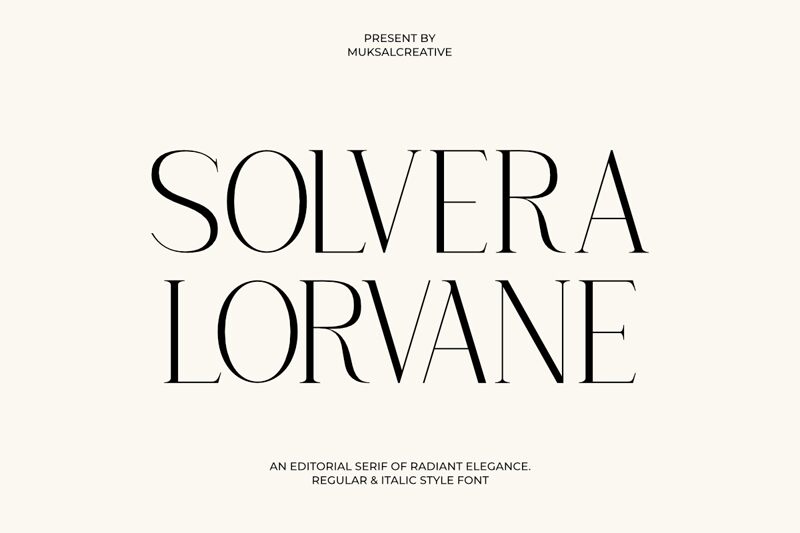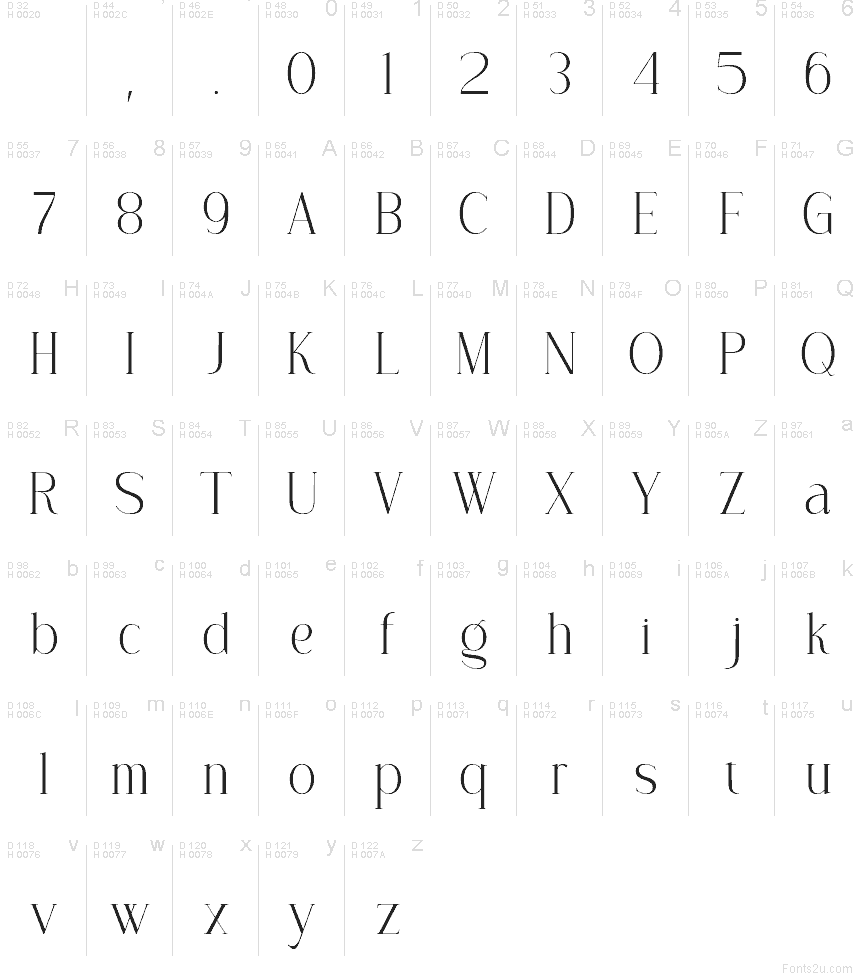
سولفيرا لورفان (Solvera Lorvane) هو خط سيريف عالي التباين من تصميم Muksal Creative، يتميز بمنحنيات طويلة ورشيقة ووصلات دقيقة للغاية تمنح الحروف مظهراً أنيقاً وفائق الجودة. تعكس الأقواس الانسيابية وتفاصيل السيريف الرفيعة إيقاعاً خفيفاً وراقياً، بعيداً عن أي صرامة تقليدية أو طابع أكاديمي جامد.
تعتبر هذه التوليفة مثالية لعلامات الأزياء، وتغليف مستحضرات التجميل، وشعارات المجوهرات، وأغلفة المجلات، وقوائم المطاعم الفاخرة، حيث تضفي اللمسات العمودية الدرامية تأثيراً قوياً بأقل عدد من الكلمات. تبرز انحناءاته الانسيابية بشكل خاص في العناوين القصيرة وشعارات الأحرف، مما يخلق تبايناً حاداً مع الصور والتصاميم المفتوحة وملصقات المنتجات الفاخرة.